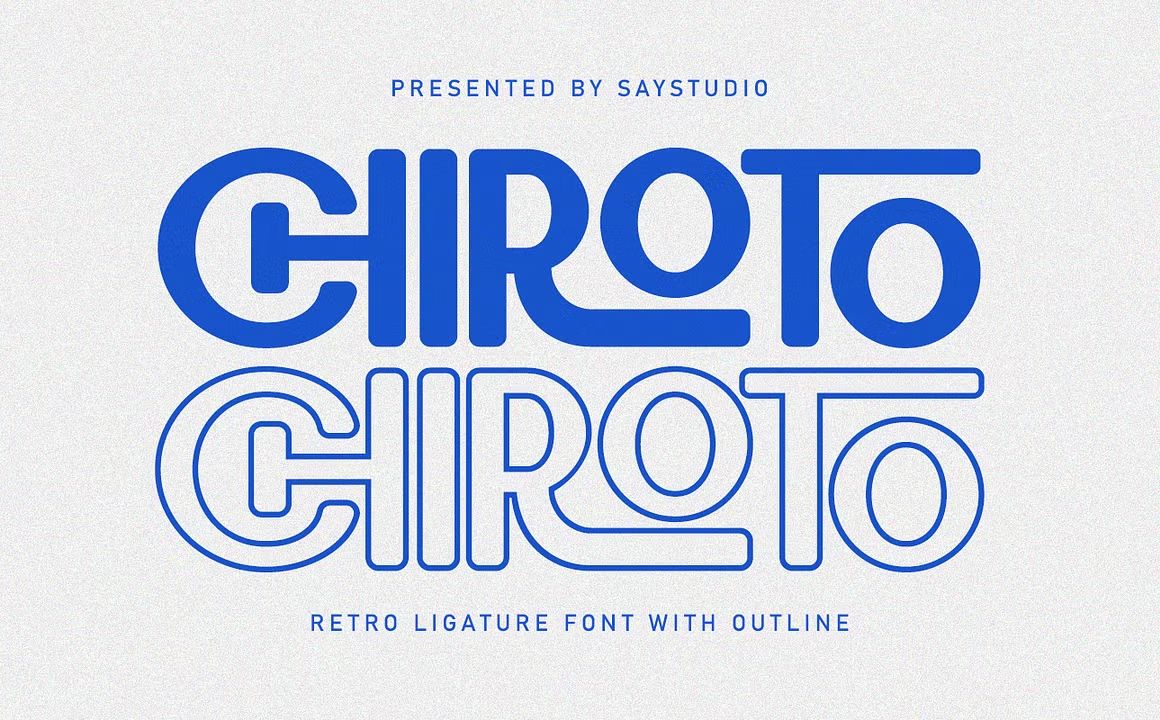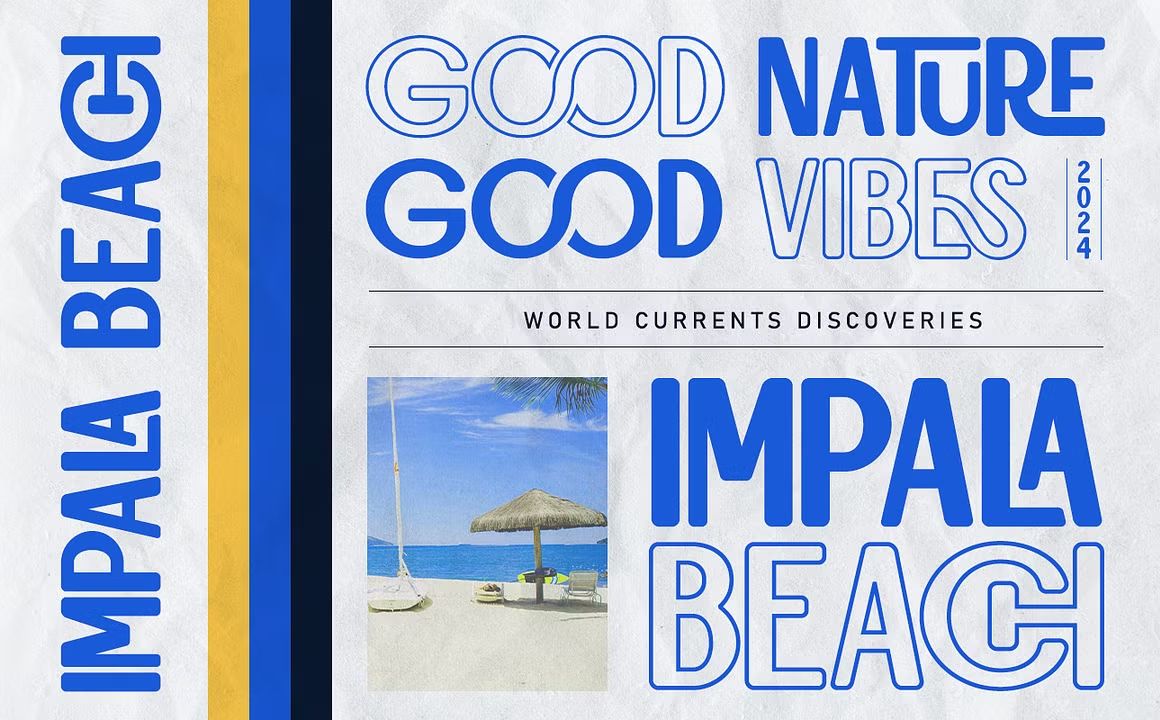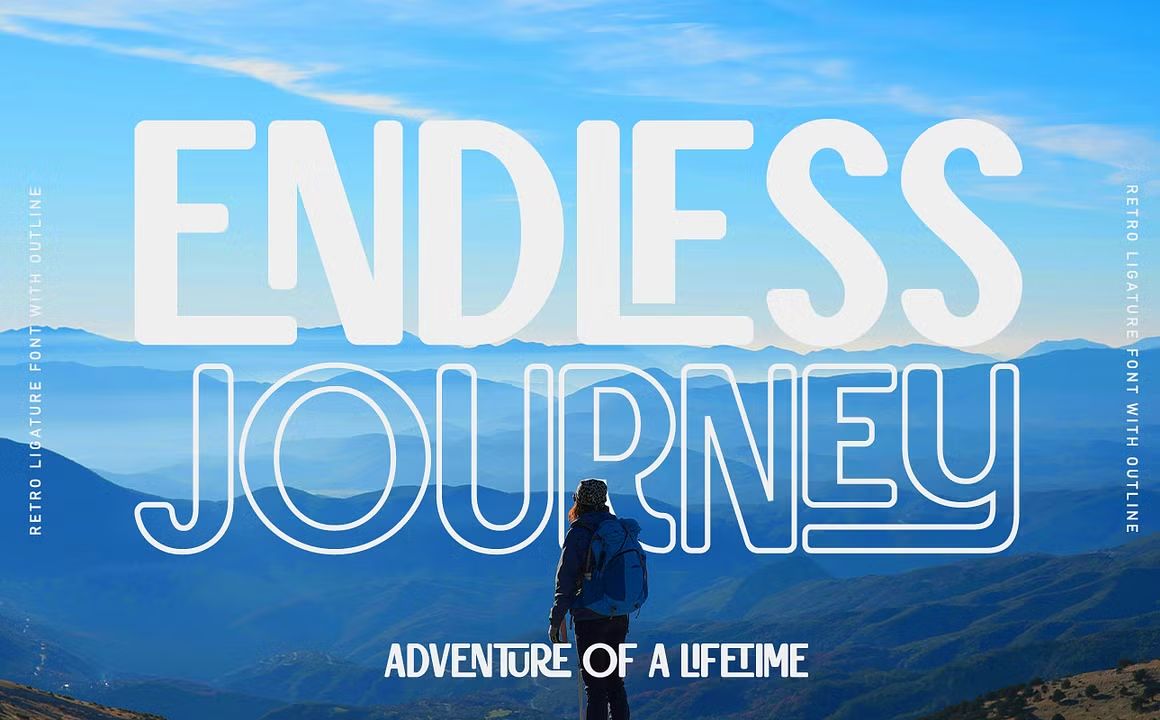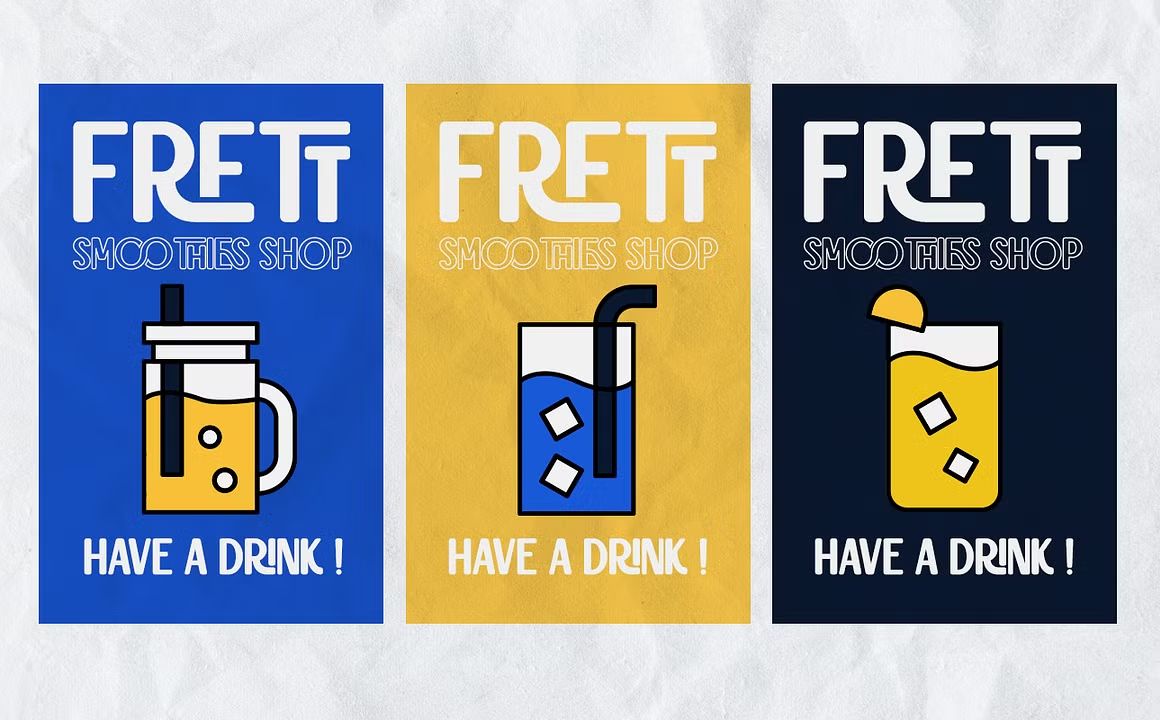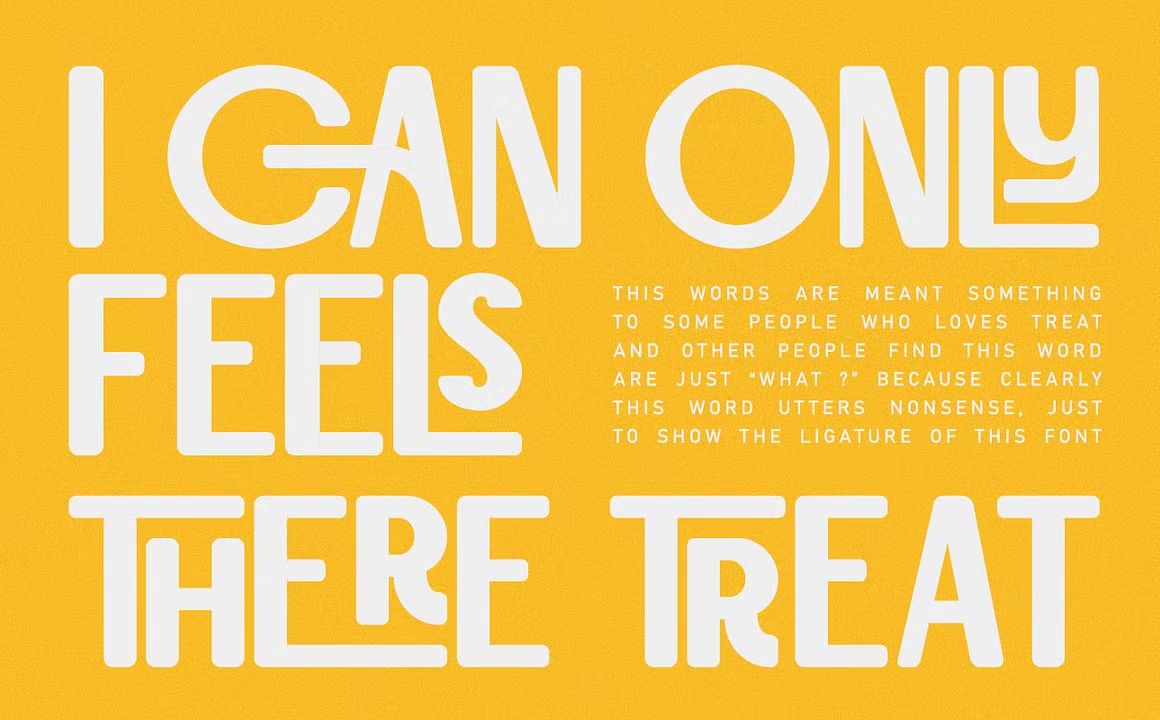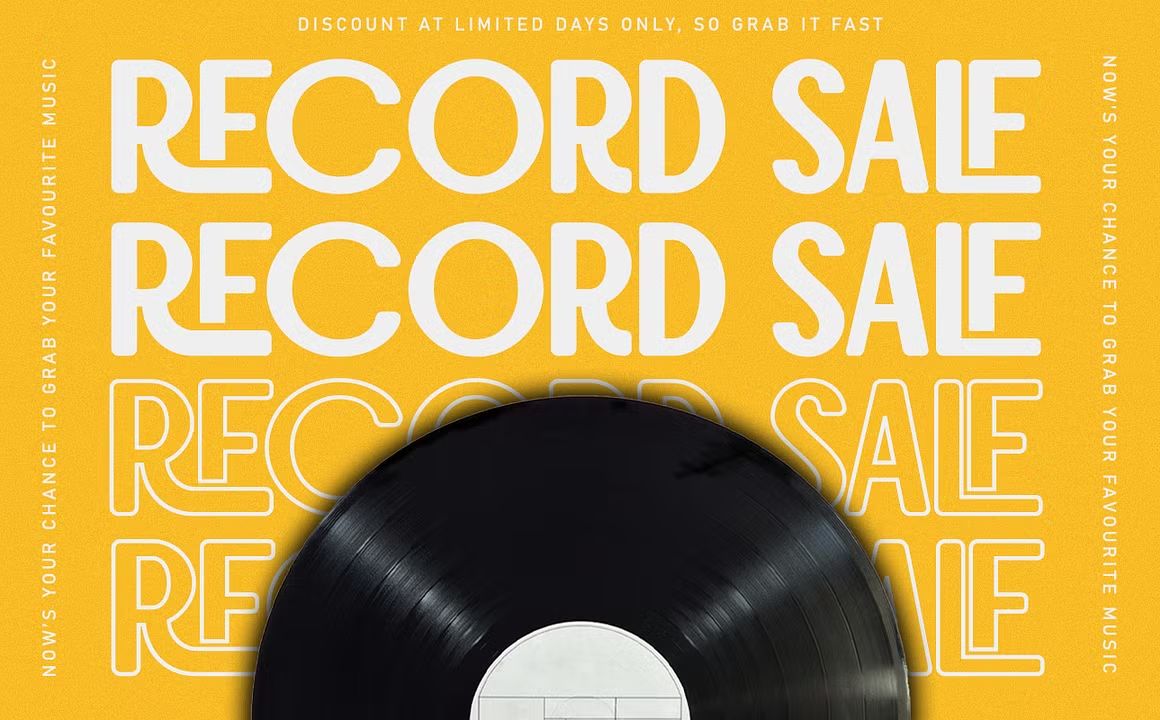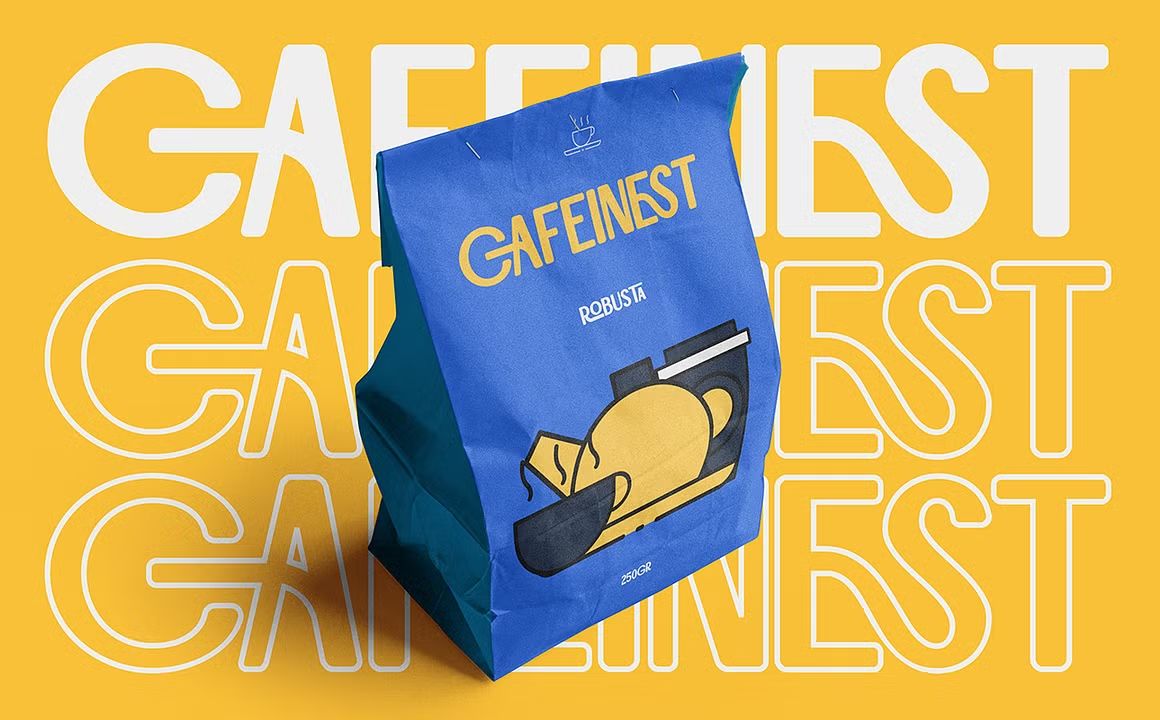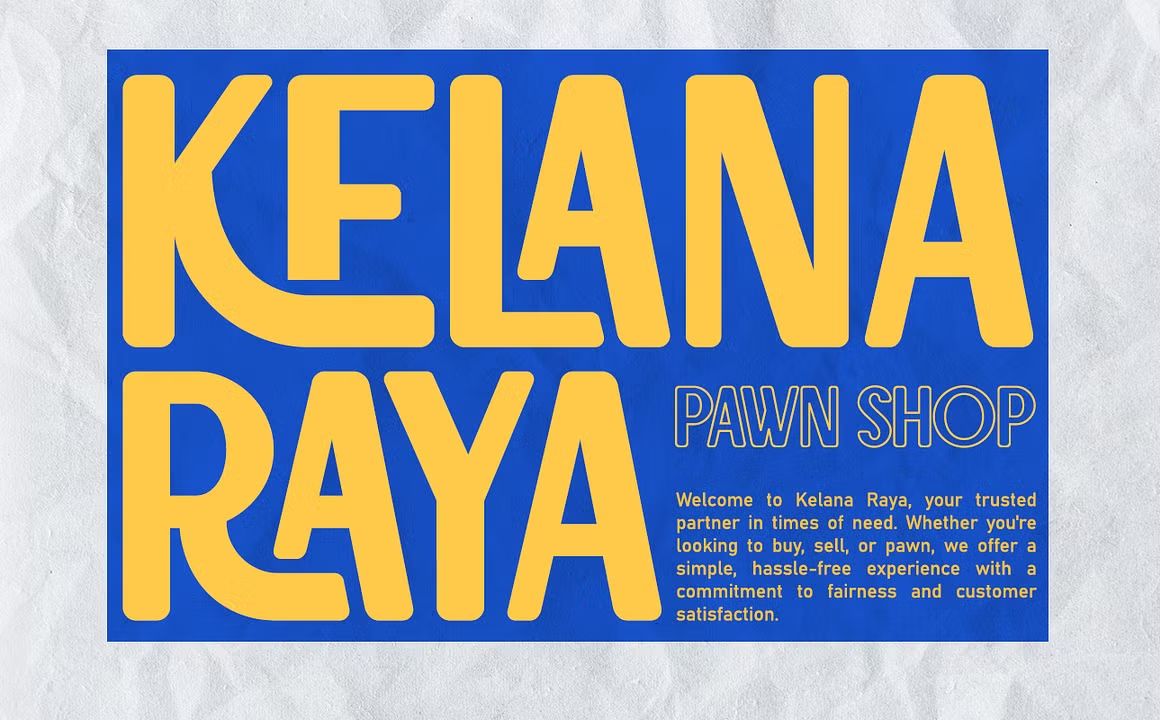
Chiroto – Sans Serif Font
Chiroto adalah font sans serif bergaya modern dengan karakter ramping, bersih, dan elegan. Didesain untuk memberikan kesan minimalis namun profesional, font ini sangat cocok untuk branding, desain korporat, editorial, web design, dan kemasan produk. Bentuk huruf yang proporsional menjadikan Chiroto tampil versatile dan mudah dibaca di berbagai ukuran.
• Sans serif ramping dengan nuansa modern dan profesional
• Cocok untuk branding, editorial, dan desain digital
• Termasuk huruf kapital, kecil, angka, dan simbol